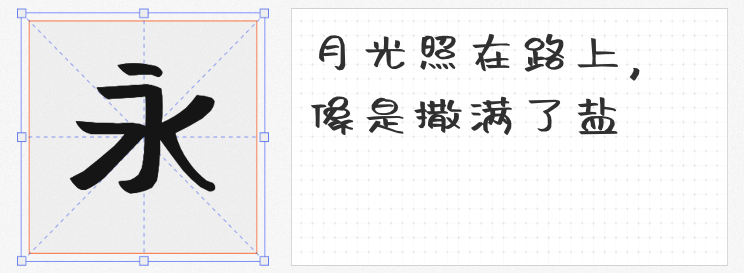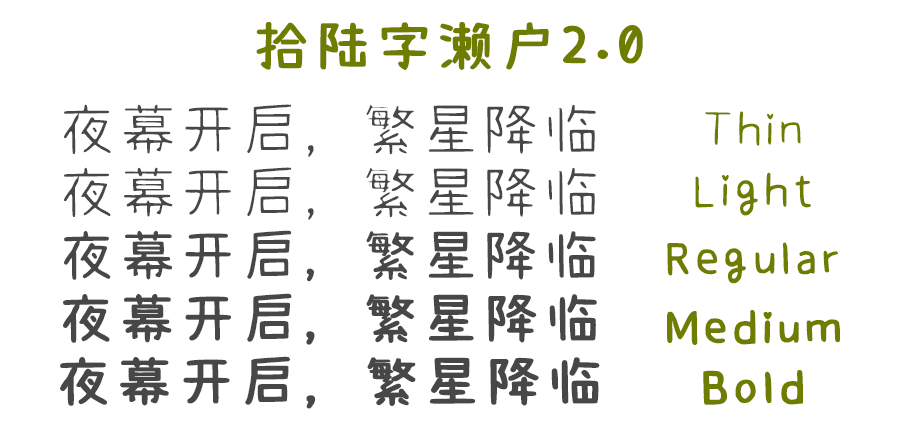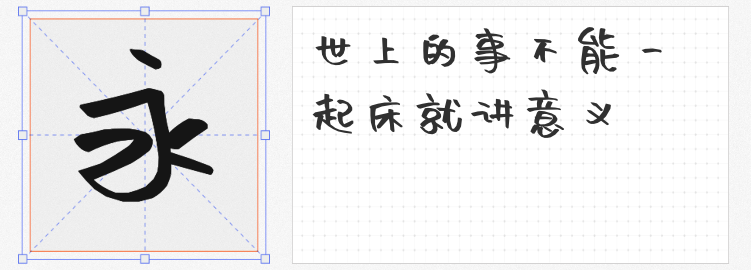
在设计的世界里,字体不仅是信息的载体,更是情感的传递者。今天,为大家推荐三款风格可爱、免费且可商用的手写字体——拾陆字濑户2.0、沐瑶随心手写体、阿朱泡泡体,它们将为你的设计作品增添一抹独特的温馨与趣味。
💞 ① 拾陆字濑户2.0
这款字体源自公众号【拾陆字】对「全濑Pro」的精心完善与再创作,并慷慨地向全社会开放免费商用权限。它包含五个细腻的字重变化,每个字重都展现出不同的韵味。轻字重时,笔画间的粗细变化清晰可见,交接处的“粘连”效果宛如水笔手写,自然流畅;重字重则显得圆润可爱,粗细均匀,为设计带来一抹童真色彩。
💓 ② 沐瑶随心手写体
这是一份爱的纪念,由作者为庆祝与妻子结婚四周年而创作。他们的爱情故事始于文字,因此,这款字体不仅是设计的元素,更是情感的见证。沐瑶随心手写体随性而不失和谐,每一笔都透露出作者的真心与妻子的柔情,为你的设计作品增添一份随性的温馨。
💝 ③ 阿朱泡泡体
发布于2019年光棍节的阿朱泡泡体,以其独特的卡通趣味和装饰色彩吸引了众多设计师的目光。其笔画随意放松,变化多端,尤其是口型偏旁被设计成“泡泡”形状,让整个字体充满了青春活力。这款字体风格鲜明,特点突出,无论是艺术设计、包装印刷,还是签名设计、图形设计,都能轻松驾驭,为你的作品带来无限创意。
🍬🍬这三款可爱的手写字体,不仅免费且可商用,更以其独特的风格和情感内涵,为你的设计作品增添一抹不可复制的温馨与趣味。不妨试试看,让它们成为你设计中的亮点吧❣️❣️❣️